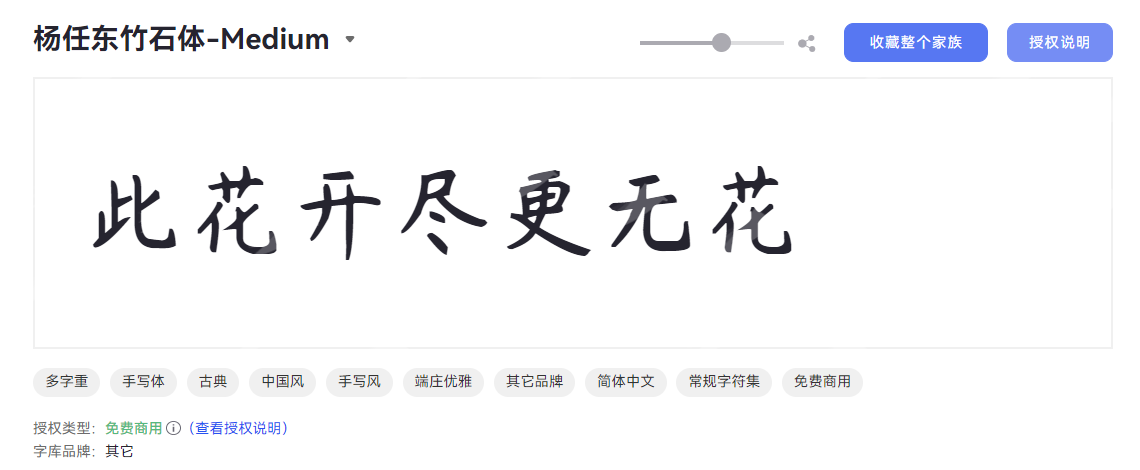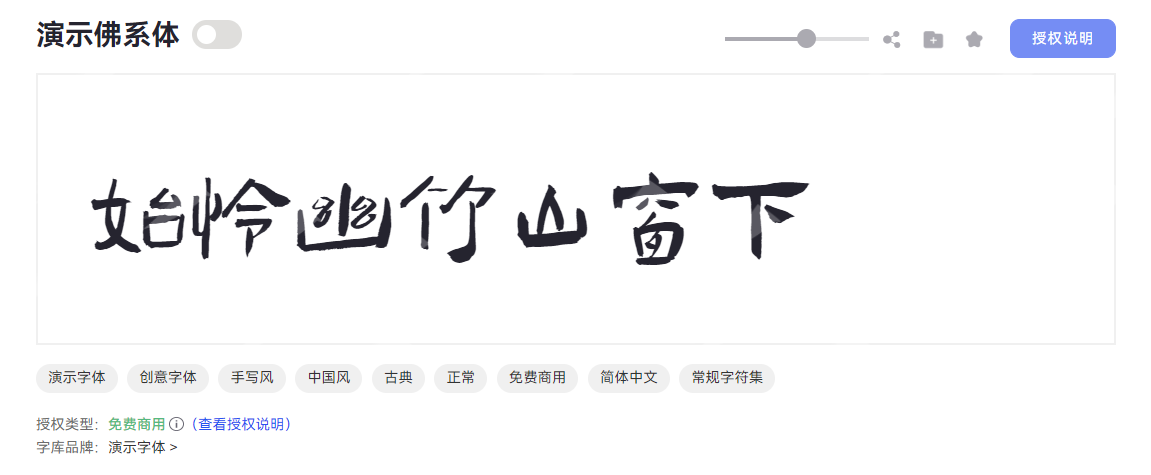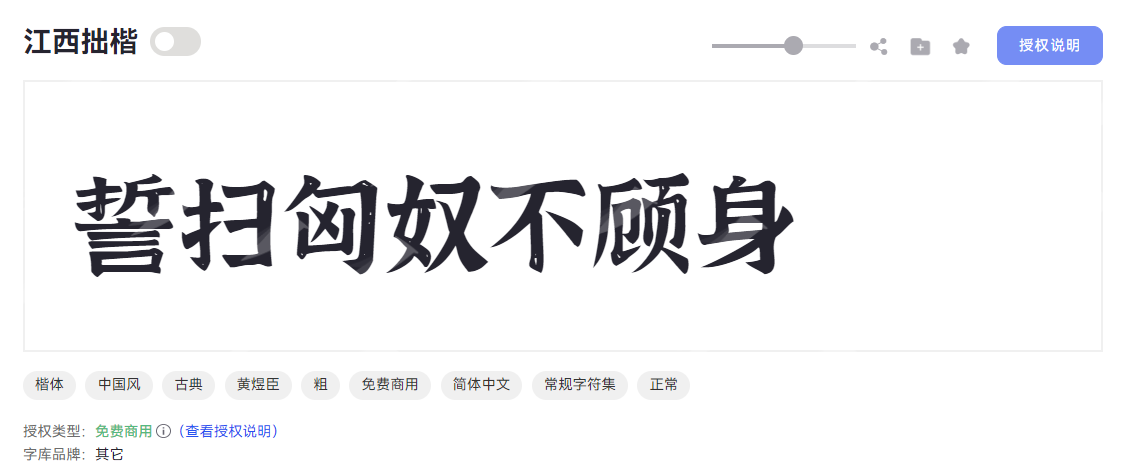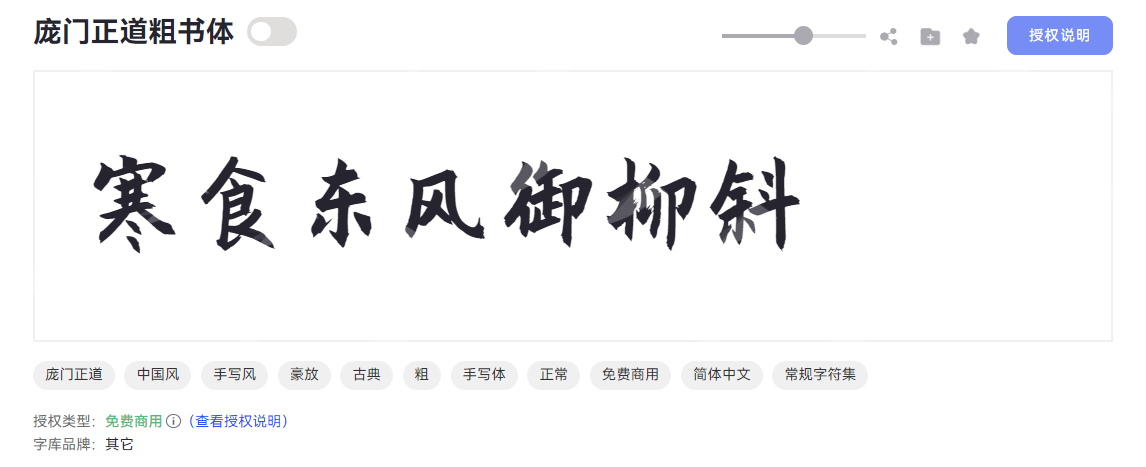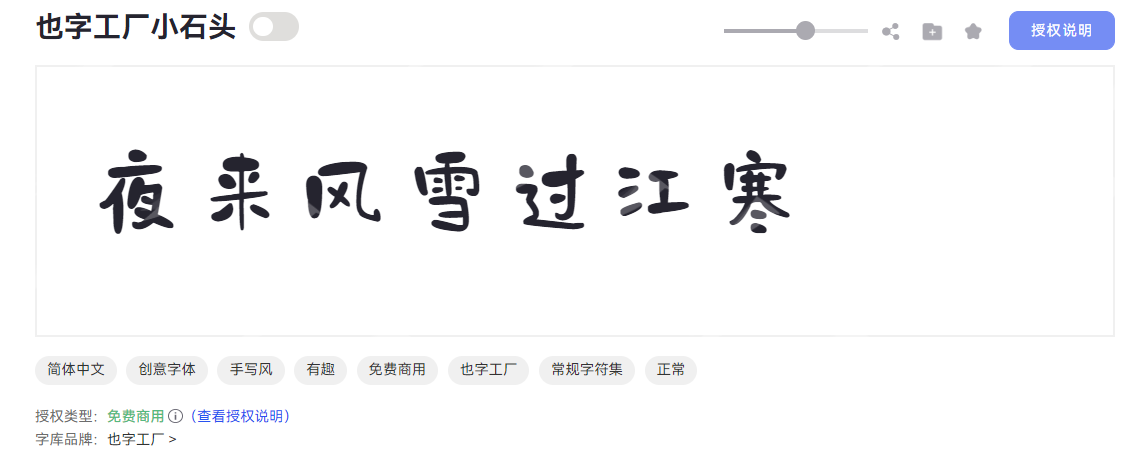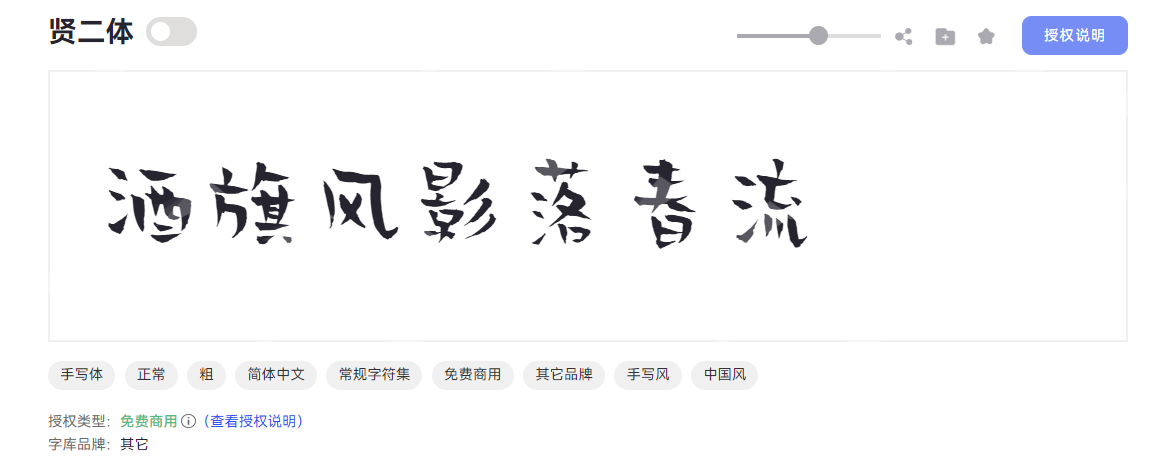
在新媒体运营、设计创作等场景中,优质的中文字体都是不可或缺的,是提升作品质感的关键要素。近年来,免费的中文字库层出不穷,资源丰富、没有版权压力、无需繁琐的安装过程,就可以获取到高颜值的中文字体。字由作为国内专业的字体管理工具,内含上万款优质字体,其中免费可商用的中文字体也有上千款,涵盖多种风格,适配所有设计场景,绝对是 2026 年获取中文字库的最佳渠道。本文将从字由官网精选 6 款高颜值、高实用性的免费中文字体介绍给大家,欢迎大家直接下载使用。
1.杨任东竹石体
杨任东竹石体是一款书法风中文字体,笔画粗细适中、舒展有力,融合了传统书法的韵味与现代字体的简约易读,文艺雅致又大气,用户使用率很高。它的字形方正偏修长,字距宽松;起笔收锋自然流畅,带有轻微毛笔笔触质感,转折处圆润柔和,无尖锐棱角;笔画细节处理细腻,放大后也能保留原始观感。
适合用于国风主题海报、茶叶包装设计、文化类公众号、书籍排版、短视频字幕等,能快速提升作品文化质感与高级感。
2.演示佛系体
演示佛系体是一款自带禅意气质的特色创意字体,以扁宽舒展的字形结构传递从容自在的视觉语言。字体采用居中重心设计,形态稳重大气又不失舒展;笔画柔和纤细,笔触自然无机械感;笔型融入柔和圆角与圆润笔触,粗实均匀的线条既保留饱满力量感,又通过圆头笔画增添亲和温度。演示佛系体最独特的就是笔画之间的断开处理,巧妙留出了字体之间的呼吸空间,让字体多了一分灵动和生命力,成为传递平和治愈心境的理想字体选择。
这款字体适配手账排版、小红书笔记封面、美食文案、治愈系海报、甜品店宣传语、母婴产品包装等,传递出温暖松弛的感觉。
3.江西拙楷
江西拙楷是经典的中国风楷体字体,保留了楷体的工整雅致,优化笔画细节适合现代排版风格,犹如古籍中的墨宝重现。字体采用方正稳健的字形结构,字形端正且均匀;方头笔画搭配均匀的线条粗细,起笔藏锋,收笔利落,横平竖直。江西拙楷由设计师黄煜臣精心打造,旨在传承传统书法美学,同时兼顾数字时代的阅读体验,将古典美学与现代设计需求巧妙融合,让每一个文字都散发着沉静典雅的东方韵味。
适合用于书籍排版、公文排版、古籍复刻、课件制作、邀请函内页等比较正式文艺的场合,能有效体现作品的文艺质感与严谨性。
4.庞门正道粗书体
庞门正道粗书体是中国风粗体手写字体,以古典手写风与豪放气韵为核心设计亮点。它的结构方正大气,重心居中稳固,视觉上平衡且富有张力;笔画粗壮厚实,墨色饱满,融入手写笔触的自然韵味,书法毛笔质感强,力量感十足;起笔与收笔处点缀细腻的顿笔装饰元素,既保留手写的灵动,又通过方头笔画端部强化力量感,尽显传统书法的豪放气质。笔画多以断开状态呈现,留白均匀,巧妙还原手写过程中的自然断连,避免机械感,让每一笔都透着随性与生动。
适用于古典主题海报、电商Banner、运动类设计、街头文创、文化类宣传物料,庞门正道粗书体可以精准传递中国风的古典底蕴与手写的温度,粗体字也能瞬间抓住用户的注意力。
5.也字工厂小石头体
小石头字体是一款兼具力量感与亲和力的创意黑体,风格呆萌潮酷,亲和力强。字形方正稳健,重心居中设计确保视觉平衡,中宫适中的比例让字体在各种字号下都保持清晰易读。这款字体最特别的一点就是笔型融入圆润转角,搭配粗重均匀的笔画线条,圆头笔画设计更添几分俏皮感,仿佛一颗颗精心打磨的小石头,既有方正棱角的稳重,又不失圆角带来的柔和。该字体字形圆钝,结构宽松;笔画采用断开式处理,巧妙打破传统黑体的紧凑感,为字体注入灵动气息,让每个字符都如同独立又相连的小石块,富有节奏感与设计巧思。
适配国潮设计、萌宠物料设计、APP 界面、可爱风海报等面向年轻群体的场景,传递出个性呆萌的氛围感与时尚感。
6.贤二体
贤二体风格俏皮可爱,是一款兼具中国风与手写质感的简体中文手写体,融合传统书法韵味与现代设计美学,形成独特的视觉风格。 字形方正稳重,笔触流畅自然,笔画夸张简化,轻盈可爱,带有 Q 版手写的感觉;笔型采用圆润处理,粗重均匀的线条配合圆头笔画,既保留手写书法的自然韵味,又通过笔画断开的设计避免连笔带来的杂乱感,展现出刚柔并济的视觉张力。
贤二体适合应用于书法作品复刻、母婴产品包装、传统节日设计、儿童绘本、少儿课件、表情包配字等场景,它兼顾艺术性和实用性,给人一种活泼轻松且富有亲和力的氛围。